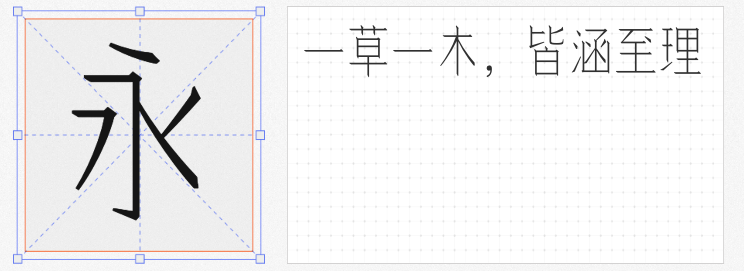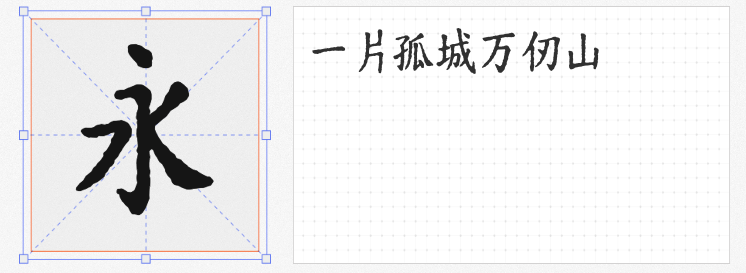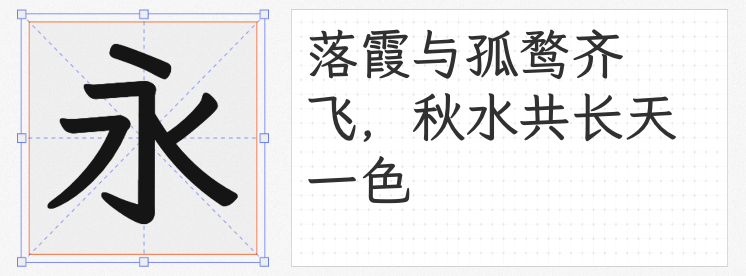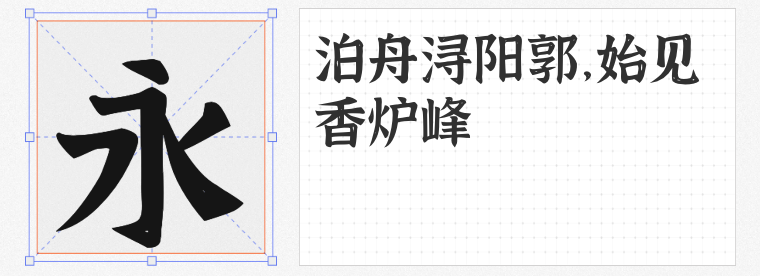
小暑至,万物渐盛。当节气海报、社交图文需要传递“温风虫鸣小暑天”的意境时,字体的选择往往决定着设计的温度。以下四款免费商用字体,以不同风格诠释夏日的雅趣与生机,助你轻松打造节气氛围感。
1. 霞鹜文楷 GB Medium
这款基于日文字体Klee One改良的字体,将仿宋的隽秀与楷体的端庄融为一体。纤细的笔画中藏着书写的力道,横竖转折处温润如玉,特别适合小暑诗词、节气科普等需要文化厚度的场景。当它承载“绿荫幽草胜花时”的诗句时,仿佛能让人闻到宣纸上淡淡的墨香,与夏日蝉鸣形成奇妙的通感。
2. 寒蝉活楷体 ConBold
若想营造“老物件”般的夏日记忆,这款带做旧效果的楷体堪称绝配。全字库正楷的扎实功底上,设计师刻意保留的斑驳纹理让字体仿佛从泛黄古籍中走出。用其设计小暑民俗插画配文时,粗犷的笔触与手绘的折扇、冰镇西瓜相映成趣,瞬间唤醒观众对旧时夏日的集体记忆。
3. 余繁细柳体
以“细”破局的这款字体,用极简的笔画勾勒出夏日的轻盈。模仿仿宋的笔画特征被压缩成更精致的形态,大字面设计让每个字都如柳枝般舒展。在制作小暑养生指南或清凉饮品海报时,纤细的字体与薄荷绿、天蓝色背景搭配,能强化“心静自然凉”的视觉暗示,让信息传递更具清凉感。
4. 江西拙楷
这款打破“规范”的手写楷体,用不完美的笔画传递最真实的夏日温度。每个字都带着书写时的微小抖动,仿佛能看见设计师在伏案创作时,额角渗出的细密汗珠。当它出现在小暑市集活动海报或家庭聚会邀请函上时,这种“不完美”恰恰成为连接观者情感的纽带,让设计更显亲切自然。
从古籍墨香到市井烟火,这四款字体如同四把钥匙,解锁了小暑设计的多元可能。在这个追求效率的时代,适当放慢节奏,让手写温度与数字设计碰撞,或许正是节气传播最动人的方式。